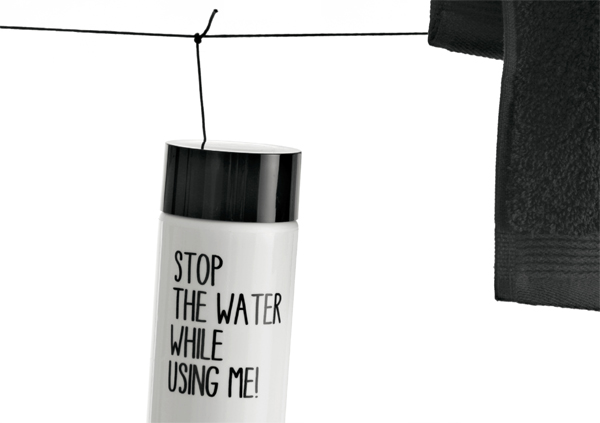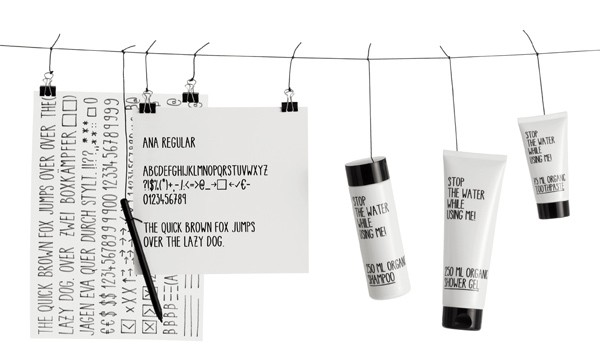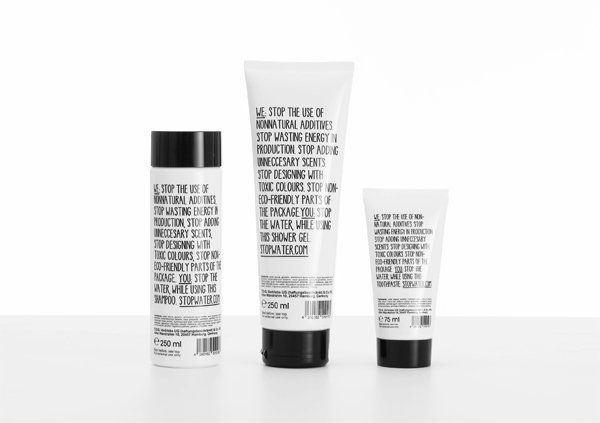
Packaging y tipografía, el mensaje se convierte en marca
Stop de water while using me!, línea cosmética de pasta de dientes, gel y champú, KOREFE (Kolle Rebbe Form und Entwicklung), 2010.
El estudio alemán KOREFE (Kolle Rebbe Form und Entwicklung) desarrolla el concepto global de diseño de la línea de productos cosméticos orgánicos Stop de water while using me! (¡Para el agua mientras me usas!), un trabajo donde naming, packaging y tipografía se unen para transformar un mensaje de responsabilidad ambiental en la propia marca.
Stop the water_
Stop de water while using me!, KOREFE (Kolle Rebbe Form und Entwicklung), 2010.
El diseño, en blanco y negro, sin otro recurso gráfico que el lettering, transmite la originalidad y austeridad bien entendida del producto. El uso destacado de la tipografía manual pone de manifiesto el carácter personal y apela directamente al consumidor.
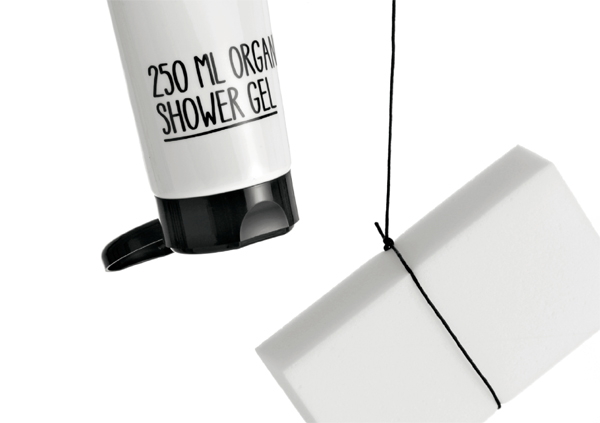
Stop de water while using me!, KOREFE (Kolle Rebbe Form und Entwicklung), 2010.
Este proyecto de identidad realizado para la empresa de Hamburgo T.D.G. Vertriebs UG (haftungsbeschränkt) & Co. ha sido ganador de numerosos galardones entre los que se encuentran dos Red Dot, IF Packaging Oro, Penta Award Plata o nominaciones a los Cannes Lion y Eurobest.
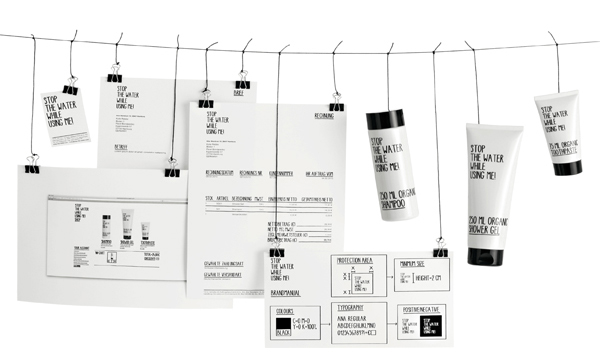
Stop de water while using me!, línea cosmética de pasta de dientes, gel y champú, KOREFE (Kolle Rebbe Form und Entwicklung), 2010.
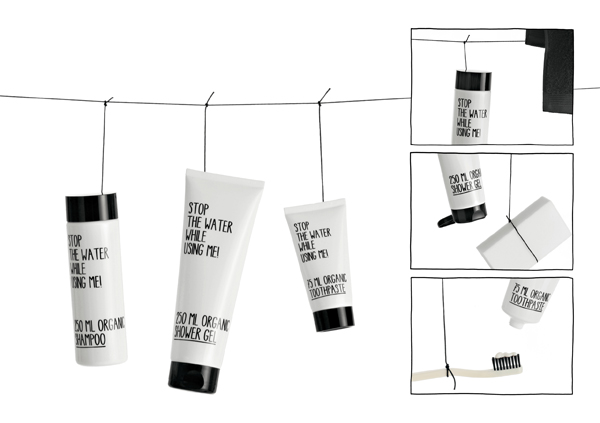
Stop de water while using me!, KOREFE (Kolle Rebbe Form und Entwicklung), 2010.
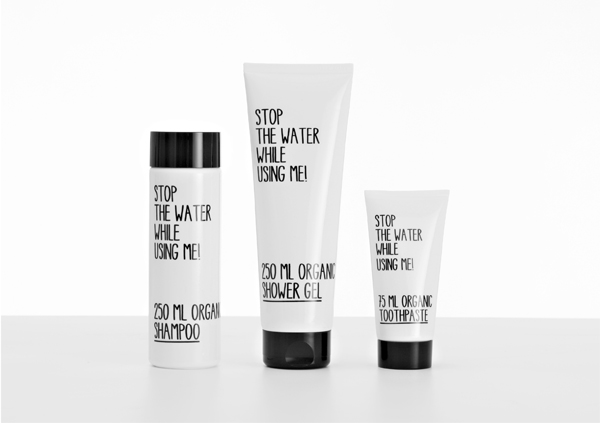
Stop the water_Stop de water while using me!, KOREFE (Kolle Rebbe Form und Entwicklung), 2010.